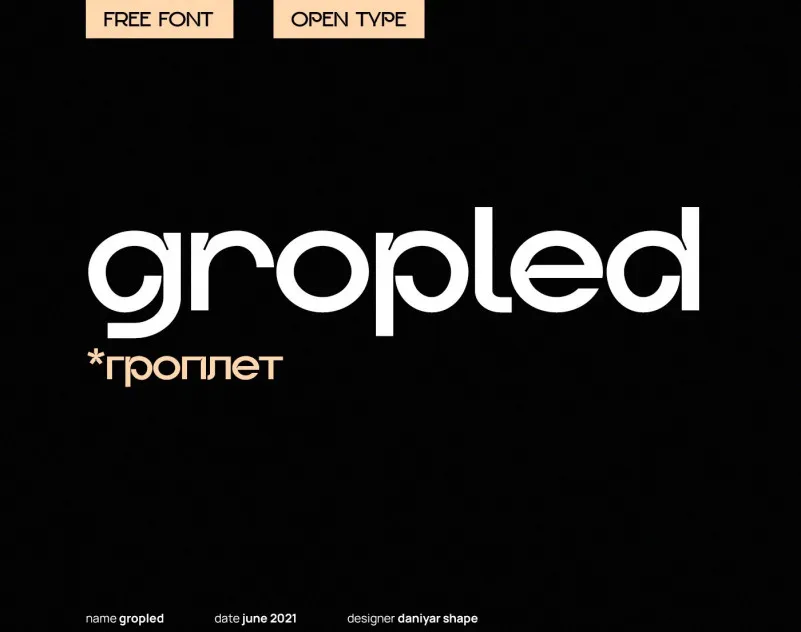
Gropled Font – Fonte Grátis
Gropled Font
A Gropled Font é uma escolha perfeita para projetos que exigem legibilidade, simplicidade e praticidade. Desenvolvida pela Daniyar Shape no formato de fonte sans serif geométrica, ela se destaca pela sua facilidade de uso e aplicação em diversos ambientes. Essa fonte está especialmente adaptada para situações formais como seminários, promoções, logos, banners e design de marca, além de ser ótima para textos informacionais ou citações. Suas linhas retas e claras garantem que sua mensagem seja clara e persuasiva em qualquer situação. Seja você um designer, editor de conteúdo ou qualquer um que precise de uma fonte fácil de usar para seus projetos formais, a Gropled Font é a escolha certa para maximizar a eficiência do seu trabalho.